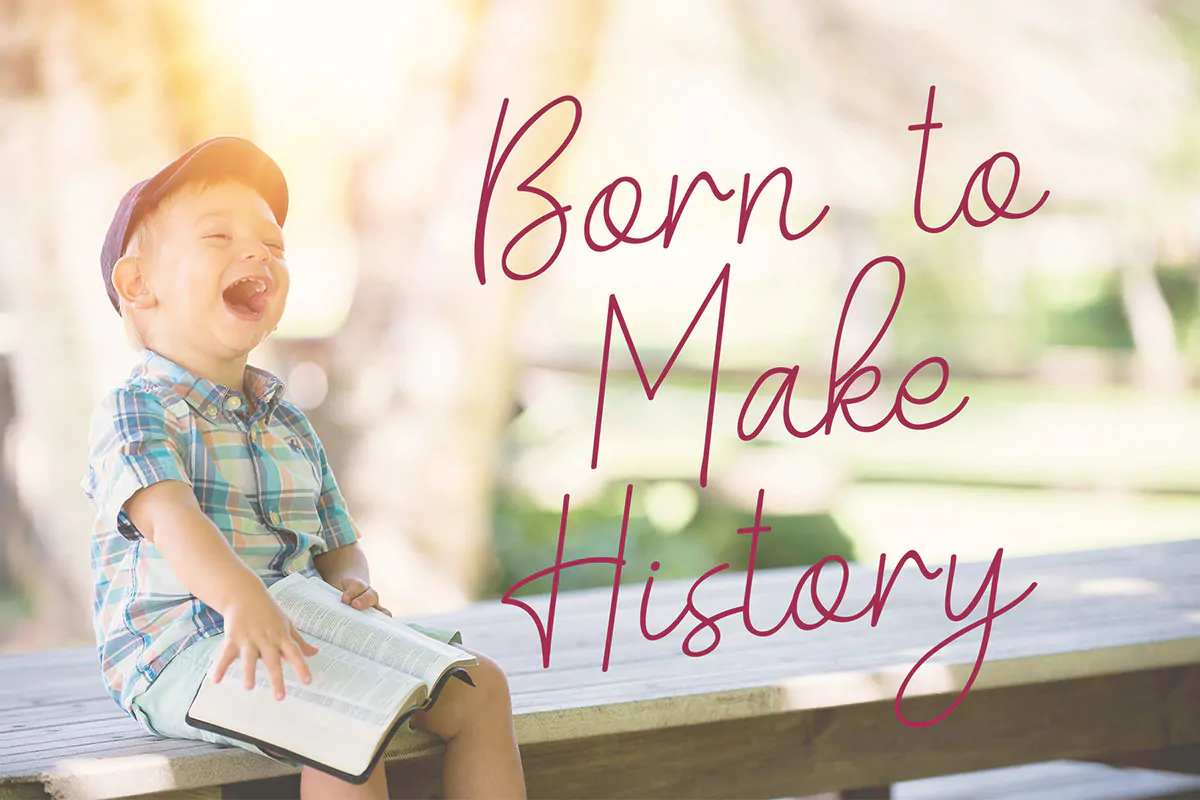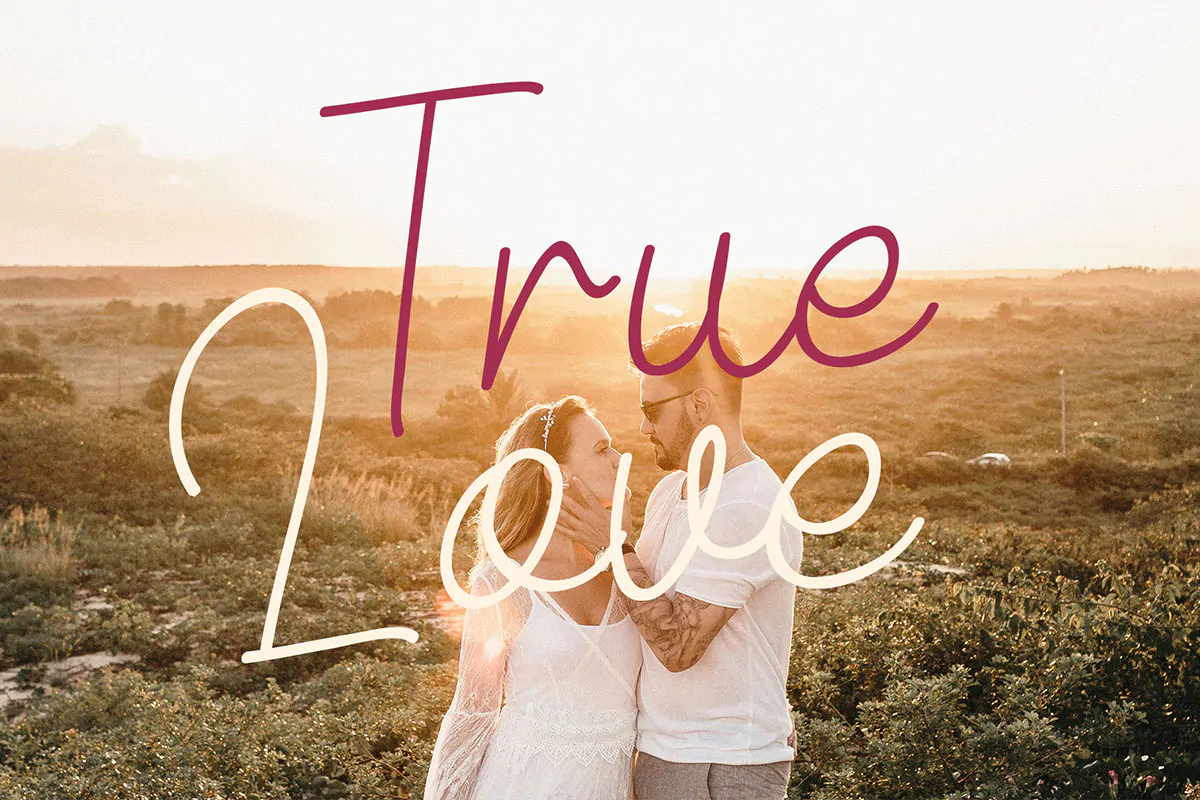
فونت دستنویس باریک Belandia
فونت دستنویس باریک انگلیسی
فونت دستنویس باریک Belandia یک قلم انگلیسی فوق العاده زیبا است که میتوانید از آن در طرحهای گرافیکی مختلف استفاده کنید.
برای تایپوگرافی، پوستر، هویت بصری و محتوای چاپی یا دیجیتال قابل استفاده است.